CSS font-style 속성
font-style 속성은 대부분 기울임꼴 텍스트를 지정하는 데 사용된다.
이 속성에는 세 가지 값이 있다:
- normal - 텍스트가 정상적으로 표시됩니다
- italic - 텍스트가 기울임꼴로 표시됩니다
- oblique - 텍스트가 "편향"입니다(사선은 기울어짐). 이탤릭체와 비슷하지만 덜 지원됨)
CSS font-weight 속성
font-weight 속성은 글꼴의 가중치를 지정한다:
CSS font-weight 속성값에 normal, lighter, bold, 900값을 설정하였을 경우 아래 그림과 같이 화면에 출력이 된다.
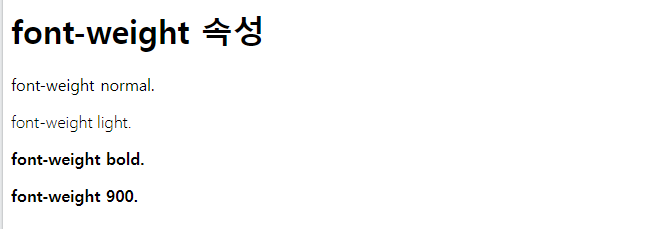
CSS font-varient 속성
font-varient 속성은 텍스트를 작은 대문자로 표시할지 여부를 지정한다.
작은 대문자 글꼴에서는 모든 소문자가 대문자로 변환된다. 그러나 변환된 대문자는 텍스트의 원래 대문자보다 작은 글꼴 크기로 나타난다.
CSS font-varient 속성값에 normal과 small-caps 값을 설정하였을 경우, 출력되는 화면은 아래 그림과 같다.
small-cpas로 설정하면 영문은 대문자로 변환되고 크기는 원래 대문자 크기보다 작게 출력되는 것을 확인할 수 있다.
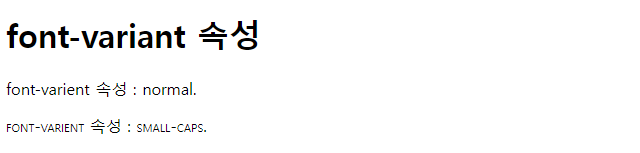
지금까지 font-weight와 font-varient 속성값에 대한 개념과 실습을 간단히 살펴보았다.